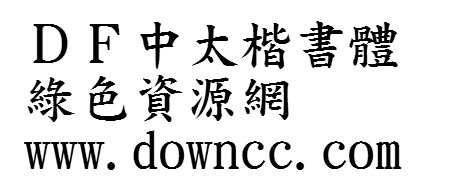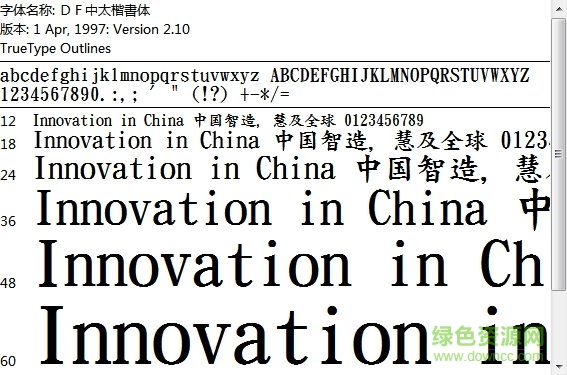
df中太楷書體是由華康字型公司推出的一款楷體書法字體,字間距較為疏松,形態(tài)端正分明,線條純粹而精簡,給人深沉大氣的視覺體驗(yàn),喜歡的朋友快來綠色資源網(wǎng)試試吧!
中太楷書體自帶粗黑設(shè)計(jì),容易獲取大家的目光,造型中正,中文字體采用了楷書字體風(fēng)格,英文字體與系統(tǒng)字體較為接近,有著不錯(cuò)的藝術(shù)設(shè)計(jì)效果!
中太楷書體來與臺(tái)灣的華康字型,風(fēng)格簡約大方,給人嚴(yán)肅穩(wěn)重的藝術(shù)美感,讓你的平面設(shè)計(jì)、包裝設(shè)計(jì)、藝術(shù)設(shè)計(jì)更加出彩!